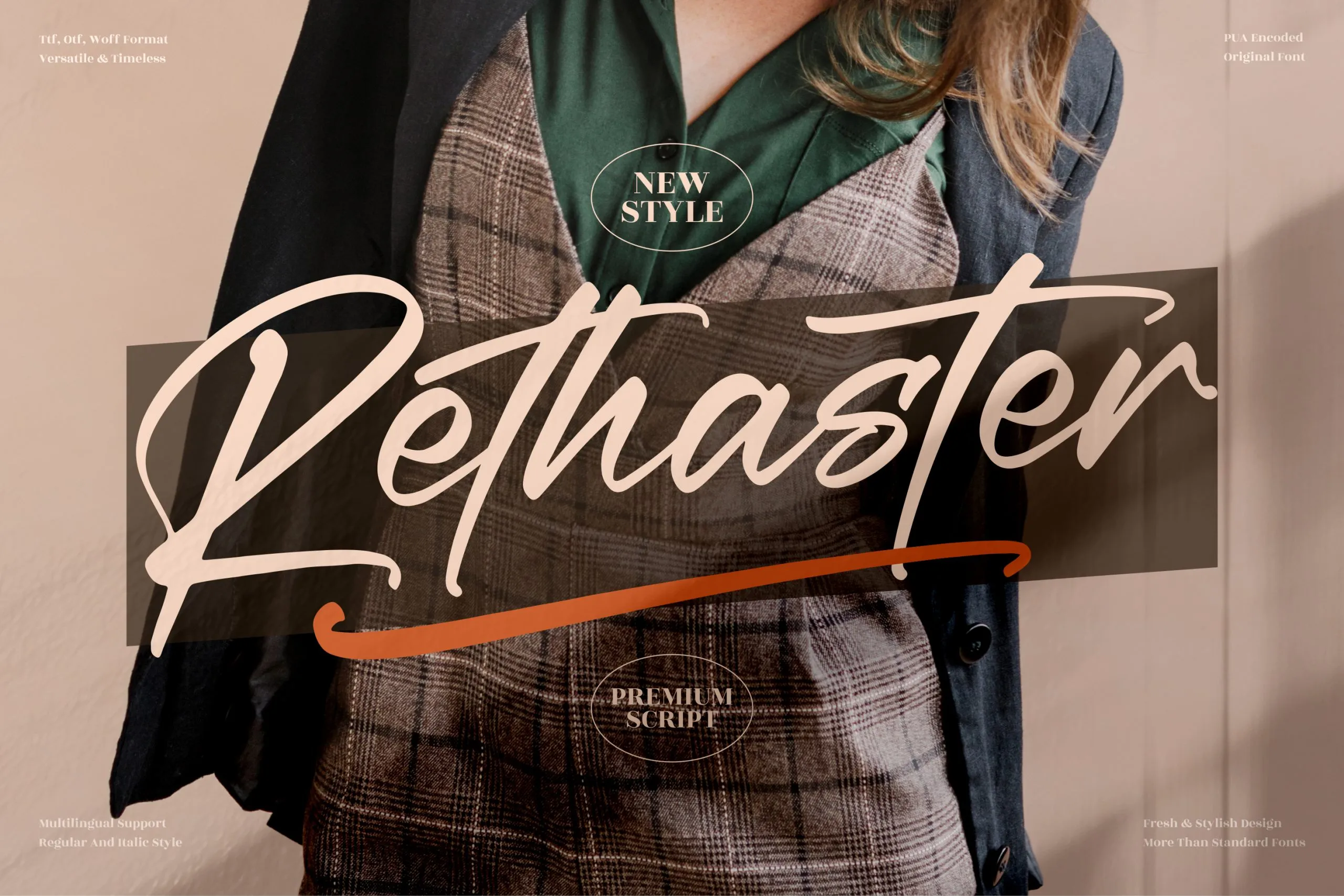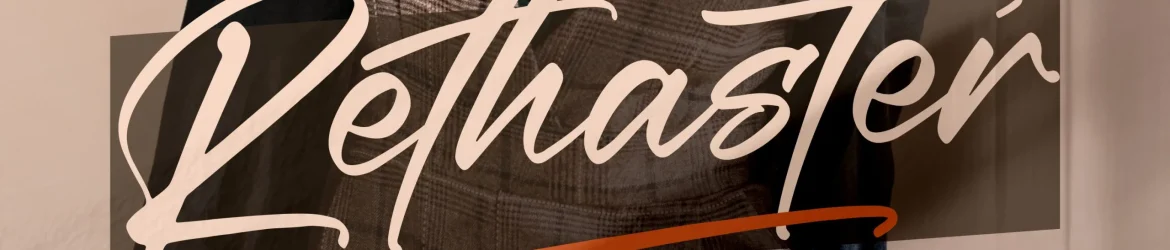
Rethaster Font – Download Grátis
A fonte ‘Rethaster Font’ é uma opção premium perfeita para quem busca um toque elegante no seu trabalho artístico. Esta fonte é especialmente concebida para aplicação em logotipos, projetos de identidade corporativa, designs de mobílias e embalagens de produtos, desde etiquetas até cartões de visita, convites e encomendas personalizadas. Com sua sofisticada natureza, a ‘Rethaster Font’ é perfeita para criações como capas de livros, materiais promocionais, fotografias e até mesmo em designs exclusivos ou eventos especiais. Seja você designer de gráficos, fotógrafo ou criativo de qualquer área do design, essa fonte oferece um toque autêntico e elegante que complementará perfeitamente suas criações. A ‘Rethaster Font’ foi projetada para dar um brilho extra a sua arte, garantindo um acabamento impecável em qualquer projeto. Seja você criando um produto de luxo ou um design artístico único, esta fonte atende a necessidade de um toque final sofisticado e premium.